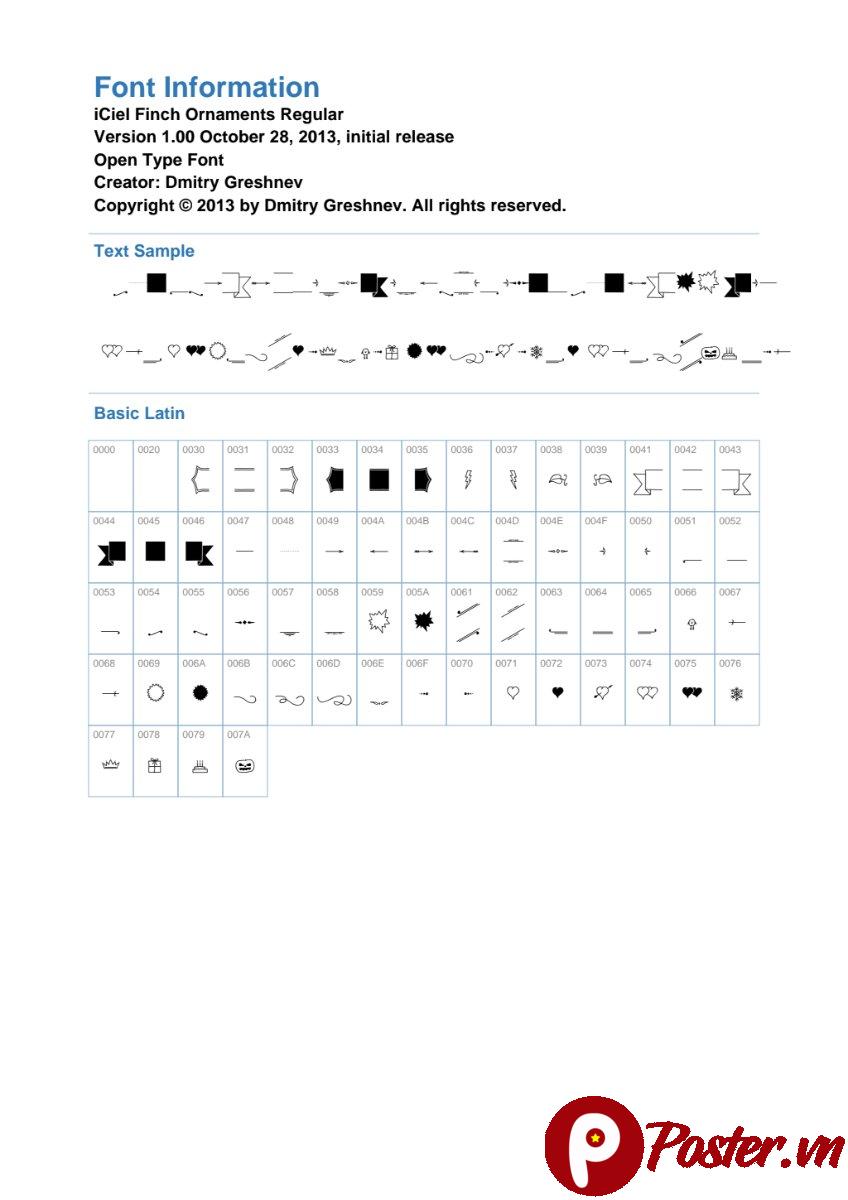
Font iCiel Finch Ornaments. Khám phá font iCiel Finch Ornaments, một bộ font trang trí độc đáo với các ký tự và biểu tượng tinh xảo, lý tưởng cho thiết kế thiệp mời, logo, và các ấn phẩm nghệ thuật. Tải ngay tại Poster.vn để tạo điểm nhấn ấn tượng cho dự án của bạn.
Trong thế giới thiết kế đồ họa, việc lựa chọn font chữ phù hợp có vai trò cực kỳ quan trọng, không chỉ truyền tải thông điệp mà còn tạo nên phong cách và cảm xúc cho toàn bộ tác phẩm. Hôm nay, Poster.vn hân hạnh giới thiệu đến bạn một tài nguyên font chữ đặc biệt: iCiel Finch Ornaments. Đây không chỉ là một font chữ thông thường mà là một bộ sưu tập các ký tự trang trí, biểu tượng và họa tiết tinh xảo, mở ra vô vàn khả năng sáng tạo cho các nhà thiết kế.
Giới thiệu về Font iCiel Finch Ornaments
iCiel Finch Ornaments là một bộ font OpenType được phát triển bởi Dmitry Greshnev, ra mắt lần đầu vào ngày 28 tháng 10 năm 2013. Đúng như tên gọi của nó, bộ font này tập trung vào các ‘ornaments’ (họa tiết trang trí) thay vì các chữ cái và số truyền thống. Điều này làm cho iCiel Finch Ornaments trở thành một công cụ đắc lực cho những ai muốn thêm các chi tiết nghệ thuật, hoa văn, hoặc biểu tượng độc đáo vào thiết kế của mình.
Với iCiel Finch Ornaments, bạn sẽ tìm thấy một thư viện phong phú các hình dạng, đường nét, và biểu tượng từ đơn giản đến phức tạp, tất cả đều được thiết kế với sự tinh tế và chuyên nghiệp. Sự đa dạng này cho phép bạn dễ dàng tạo ra các yếu tố trang trí độc đáo, từ những viền hoa văn cổ điển đến các biểu tượng hiện đại, phù hợp với nhiều phong cách thiết kế khác nhau.
Đặc điểm nổi bật của iCiel Finch Ornaments
1. Kho tàng họa tiết và biểu tượng phong phú
Điểm mạnh lớn nhất của iCiel Finch Ornaments chính là sự đa dạng của các ký tự trang trí. Thay vì các chữ cái A-Z, bạn sẽ khám phá một thế giới của các hình vẽ, hoa văn, dấu chấm, đường gạch, và các biểu tượng nhỏ. Điều này biến nó thành một công cụ lý tưởng để:
- Thiết kế viền và khung: Tạo ra các khung viền đẹp mắt cho thiệp mời, chứng chỉ, hoặc các ấn phẩm in ấn khác.
- Trang trí tiêu đề: Thêm các chi tiết nghệ thuật xung quanh tiêu đề hoặc logo để tạo điểm nhấn.
- Tạo biểu tượng độc đáo: Sử dụng các ký tự để tạo ra các biểu tượng tùy chỉnh cho website, ứng dụng, hoặc các dự án thương hiệu.
- Thiết kế hoa văn lặp lại: Dễ dàng tạo ra các mẫu hoa văn liền mạch cho background hoặc các yếu tố trang trí khác.
2. Định dạng OpenType linh hoạt
3. Chất lượng thiết kế cao
Mỗi ký tự trong iCiel Finch Ornaments đều được thiết kế tỉ mỉ, đảm bảo độ sắc nét và chi tiết cao ngay cả khi phóng to. Điều này đặc biệt quan trọng đối với các dự án in ấn đòi hỏi sự chính xác và chất lượng hình ảnh tuyệt vời. Các đường nét mượt mà và cân đối của font sẽ giúp các thiết kế của bạn trông chuyên nghiệp và thu hút hơn.
Ứng dụng của iCiel Finch Ornaments trong thiết kế
Với tính chất độc đáo của mình, iCiel Finch Ornaments có thể được ứng dụng trong rất nhiều lĩnh vực:
- Thiết kế thiệp mời và thiệp chúc mừng: Thêm các họa tiết trang trí tinh xảo để tạo nên những tấm thiệp sang trọng và cá nhân hóa.
- Thiết kế logo và branding: Sử dụng các biểu tượng hoặc hoa văn để tạo điểm nhấn độc đáo cho logo hoặc các yếu tố nhận diện thương hiệu.
- Thiết kế bao bì sản phẩm: Trang trí bao bì với các họa tiết bắt mắt để thu hút sự chú ý của khách hàng.
- Thiết kế ấn phẩm in ấn: Tạp chí, sách, poster, brochure… đều có thể trở nên sinh động và nghệ thuật hơn với các chi tiết từ font này.
- Thiết kế web và UI/UX: Tạo ra các icon, divider, hoặc các yếu tố trang trí nhỏ để cải thiện giao diện người dùng.